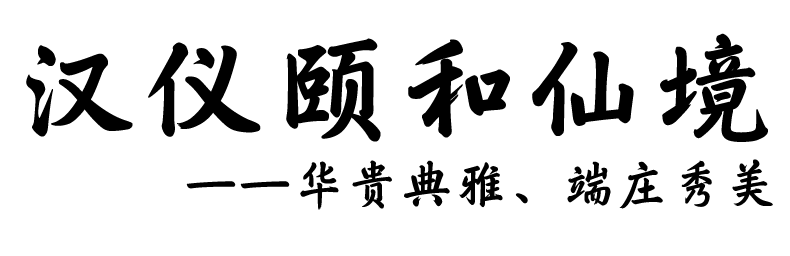
汉仪颐和仙境字体介绍,从颐和园里走出来的字体
“汉仪颐和仙境”是一款华贵典雅、端庄秀美,气韵流畅的楷书字体。汉仪颐和园体的字形修长工整,结构略有外拓。灵感来源于颐和园中的匾额碑刻文字和乾隆皇帝的书法笔迹。笔画圆润流畅,线条纤毫精谨,深稳秀逸,有赵孟頫书法的风范。
清乾隆十六年(1751 年)建颐和园万寿山昆明湖石碑。正面刻“万寿山昆明湖”六大字,背面刻《万寿山昆明湖记》,均为乾隆帝手笔。碑饰图案精美,有浓厚的民族特色。碑文记述了扩展昆明湖的目的和经过。碑两侧为吟咏湖山的乾隆御制行书诗文。
乾隆书法风格的形成是糅合了赵孟頫和董其昌两家之长,兼以宫廷之气。细观此作,子昂之气扑面而来,使转居多,少见翻折,露锋起笔,承袭二王一脉“一拓直下”的用笔方法,较之子昂,更显圆融之气。
“汉仪颐和仙境”的字形修长工整,结构略有外拓,保留了乾隆书法的特色。字面偏小,字间距大,重心略高。
在万寿山昆明湖石碑中挑选粗细相差不大、起笔收笔清晰的字进行描摹和复刻。尽量与原碑书写风格统一。
从描摹下来的字中,选取部件。如“字”来自“無”“浮”。由原碑447字再设计组合出9169个汉字字符。
汉仪颐和仙境设计过程中解决了原碑刻字面大小不一致的问题。既传承原碑的书法韵味,又在设计排版的使用中更合理优美。符合设计师排版的应用需求。
“汉仪颐和仙境”调整了部分原碑的书写字形并简化部分连笔。字体字形易辨认、易读,更加实用且适应当代的使用场景。
对复杂字形的用笔、结构进行再设计,所有细节交代的更清晰、易辨认。
“汉仪颐和仙境”入笔顿笔,出笔保留并简化了毛笔书写的肌理。
同一偏旁部首,都保留尽量多的书法用笔和结构,不同大小、粗细、倾斜角度、入笔和收笔,让字体更灵活生动,呈现手写的温度。
框形结构的字能明显看出字形外拓,按书法审美都留有开口,空间通透不死板。框形部分笔画搭接处大多错落或竖包横,丰富了线条和结构的变化,细节精致。
“汉仪颐和仙境”的西文设计具有弹性笔刷笔尖的顿挫感,基于手写和意大利体结合的风格。并依据中文行书和西文书法斯宾塞体的书写特色设计了在单词内的连笔,更匹配这款字体中文的行楷风格。
汉字行楷,每个字为独立存在,连笔在单个字内呈现。西文斯宾塞体,以一个单词为独立单元,连笔在单词内连接。结合中西文书法的特色,汉仪颐和园体选取了以单词为单元进行连笔的设计。
“汉仪颐和仙境”的西文设计与中文设计搭配和谐统一。如中文笔画的搭接、起笔顿笔、飞白等都有在西文设计中体现出来。
详尽的版面测试解决字母倾斜度、手写连笔带来的间距问题。调整字母间的距离,词间距,字母和标点符号的间距,字母和数字的间距,以及和中文简繁体匹配的大小间距。
中文主创设计师
刘宇
中文团队
张磊磊 刘金乾 何翔晖 杜姝逸
西文设计
刘翛瑀